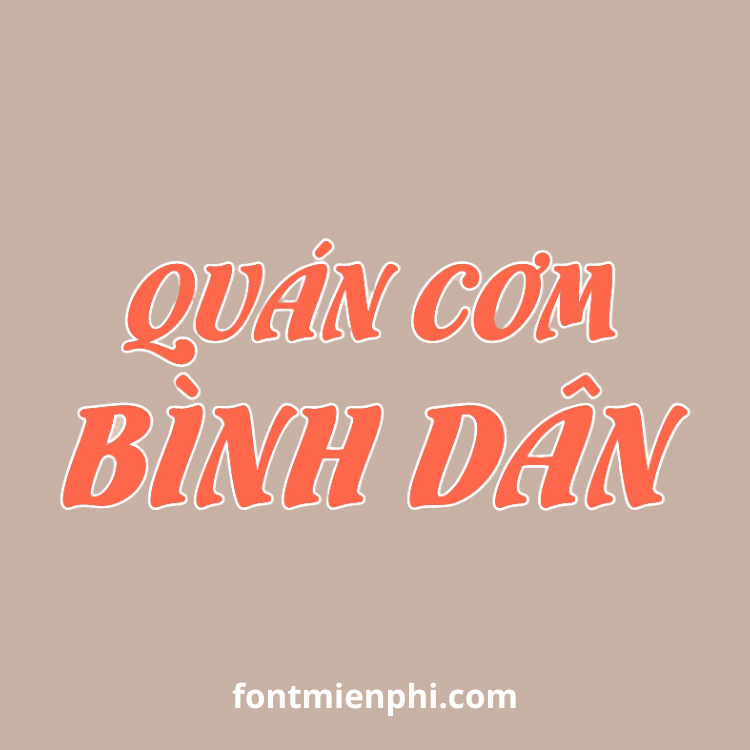
Font Việt Hóa UTM Flamenco – Vũ Điệu Nét Chữ Đầy Cảm Xúc
Giới thiệu nổi bật:
UTM Flamenco là font chữ script việt hóa đầy nghệ thuật, lấy cảm hứng từ điệu nhạc Flamenco cuồng nhiệt của Tây Ban Nha. Với những nét chữ uyển chuyển, bay bổng tựa vũ điệu, font chữ này mang đến sức sống mãnh liệt cho mọi thiết kế.
Đặc điểm ấn tượng:
Nét chữ mềm mại nhưng đầy nội lực – Kết hợp hoàn hảo giữa sự duyên dáng và cá tính
Hỗ trợ đầy đủ tiếng Việt – Giữ trọn vẻ đẹp nghệ thuật khi sử dụng dấu
2 phiên bản (Regular và Bold) – Linh hoạt cho nhiều phong cách thiết kế
️ Tối ưu cho headline – Đẹp nhất ở kích thước lớn
Ứng dụng nghệ thuật:
- Thiết kế poster ca nhạc, sự kiện nghệ thuật
- Logo thương hiệu sáng tạo, quán cà phê nghệ thuật
- Thiệp mời đám cưới phong cách bohemian
- Bao bì sản phẩm thủ công mỹ nghệ
UTM Flamenco – “Mỗi nét chữ là một bước nhảy đầy đam mê!”